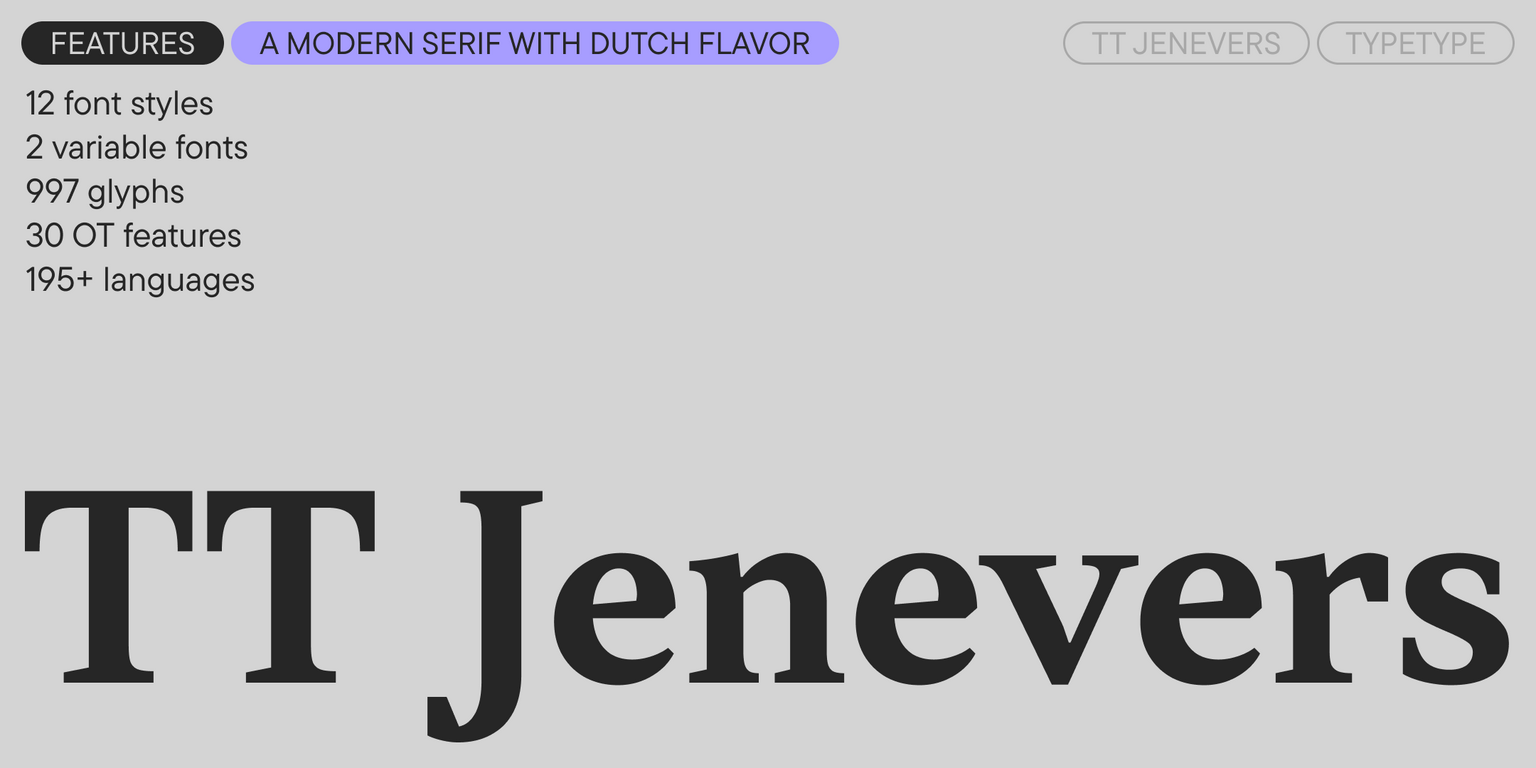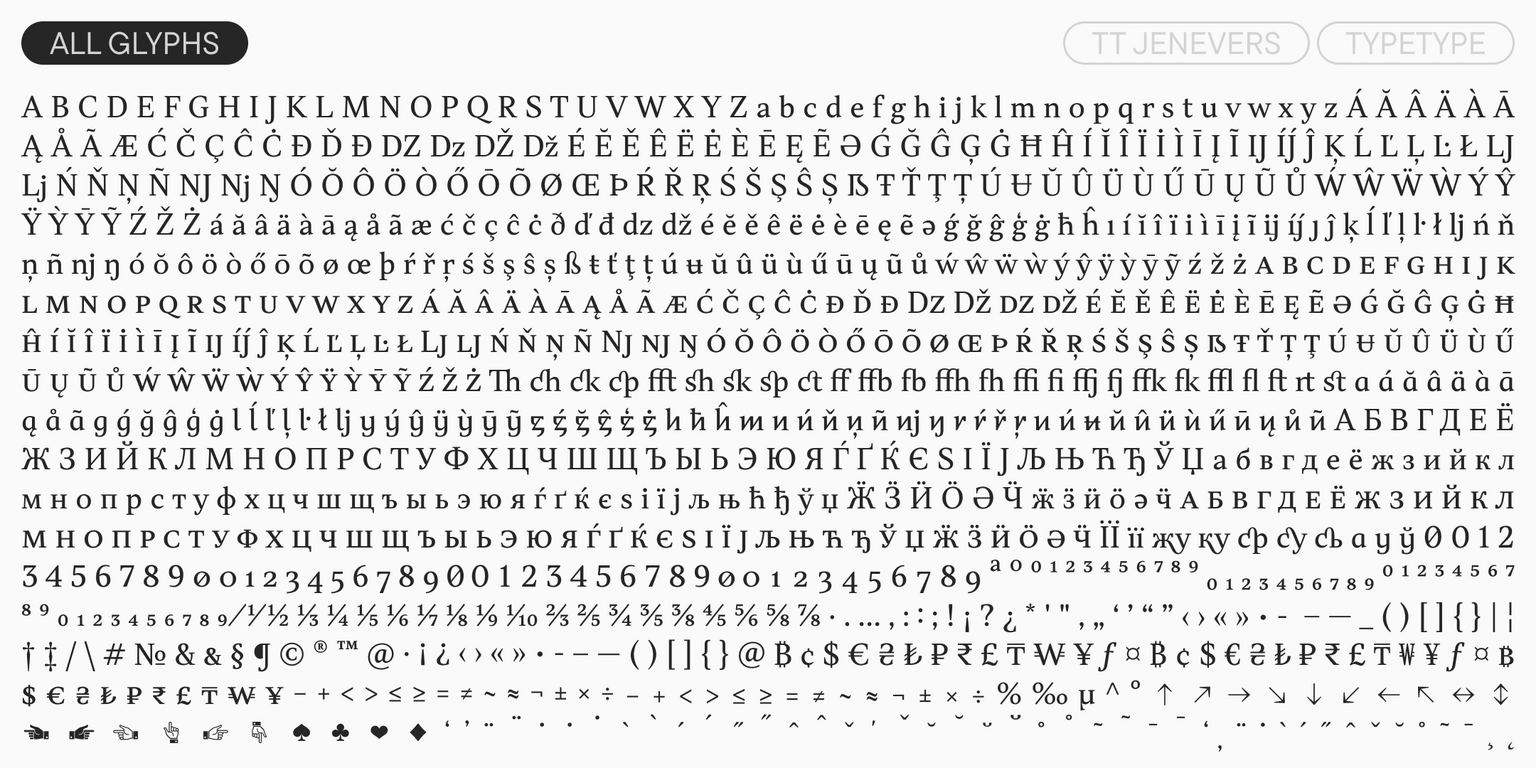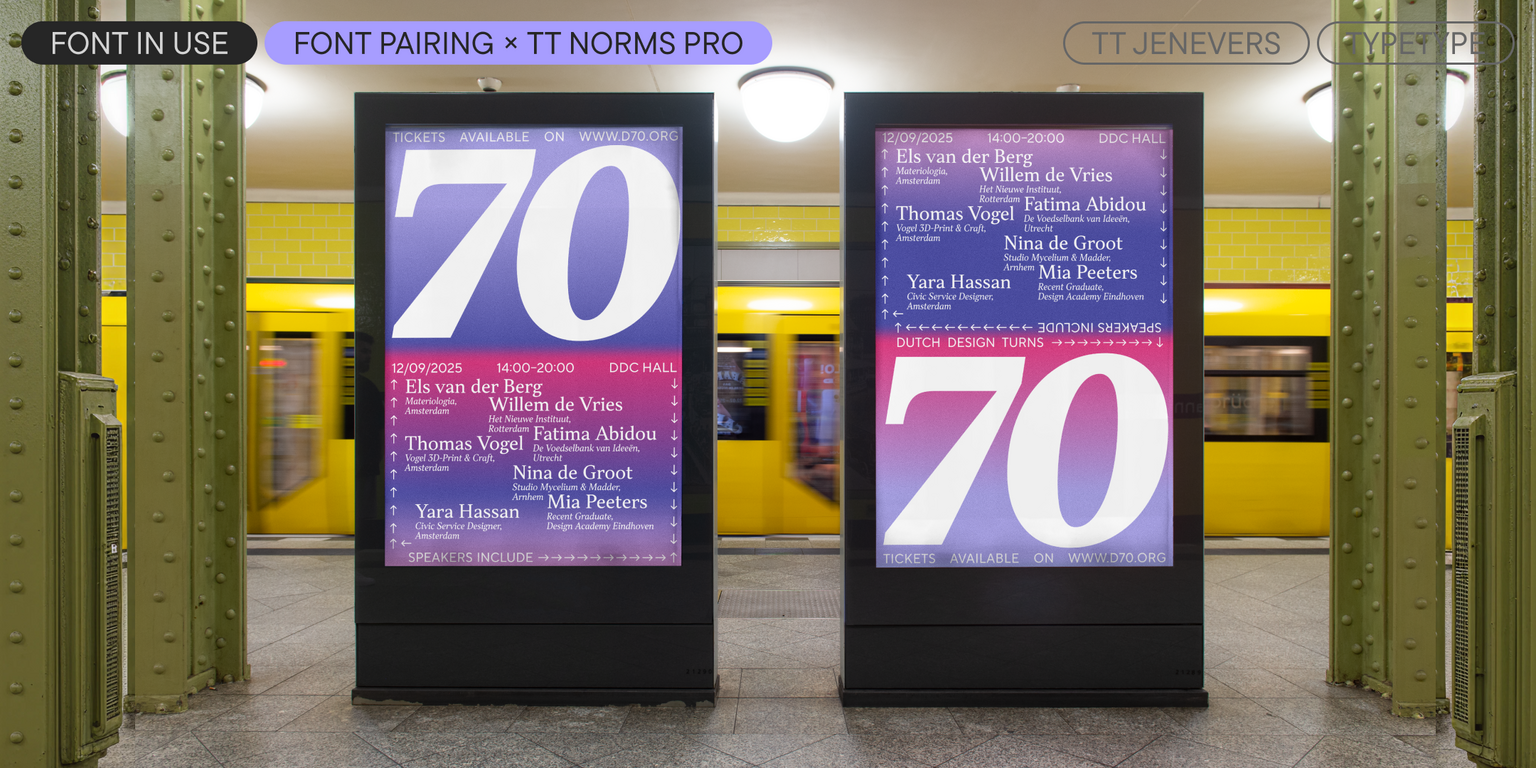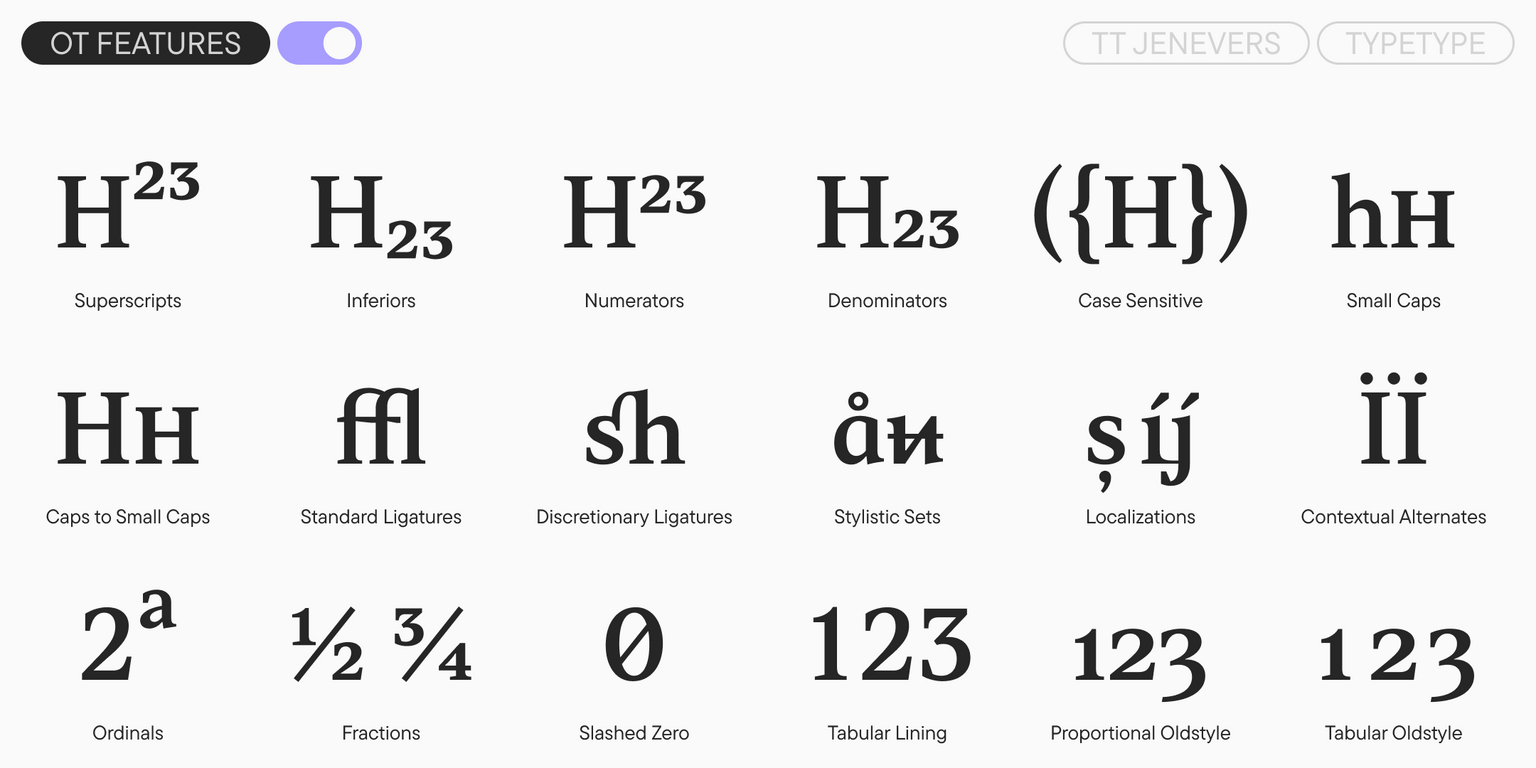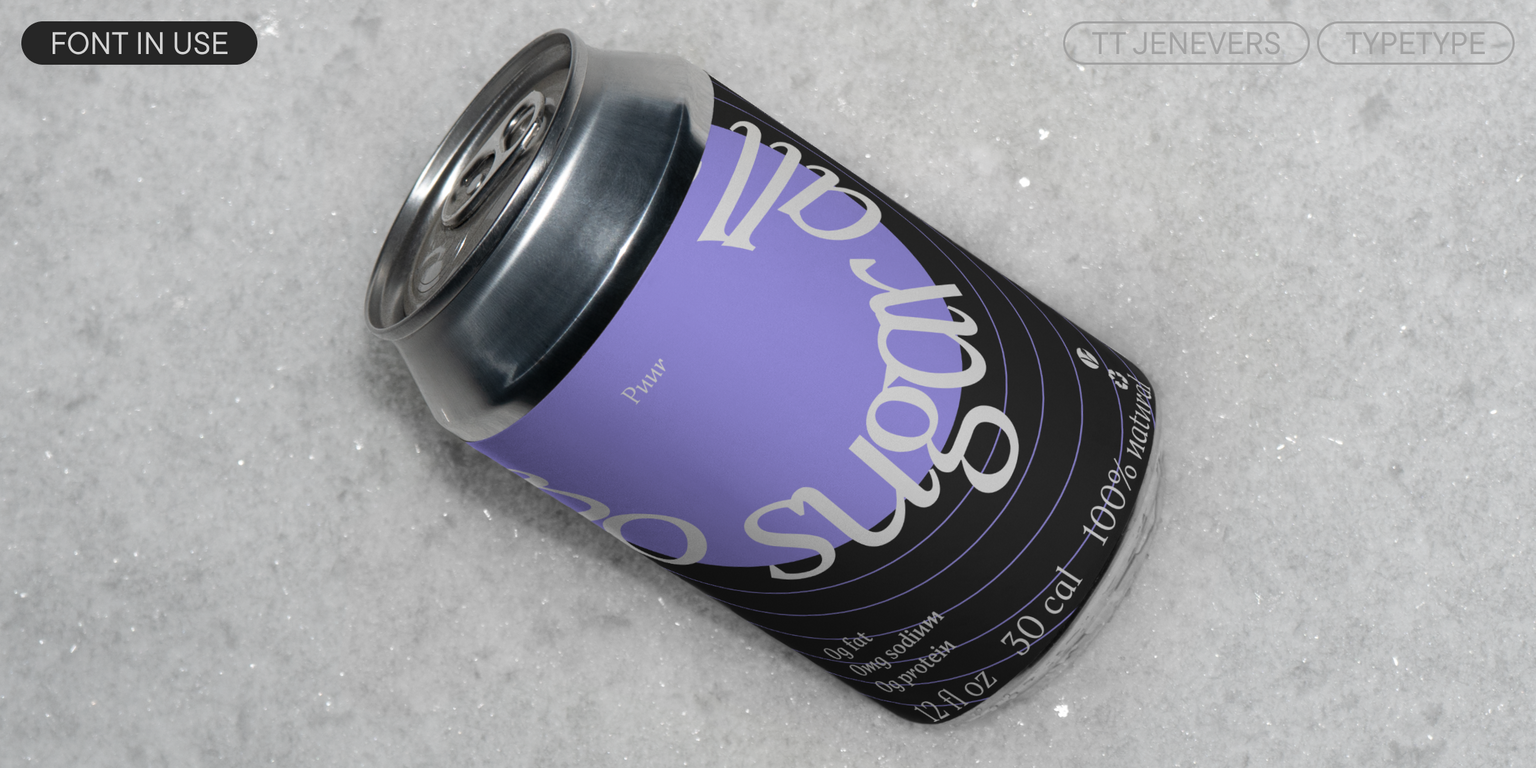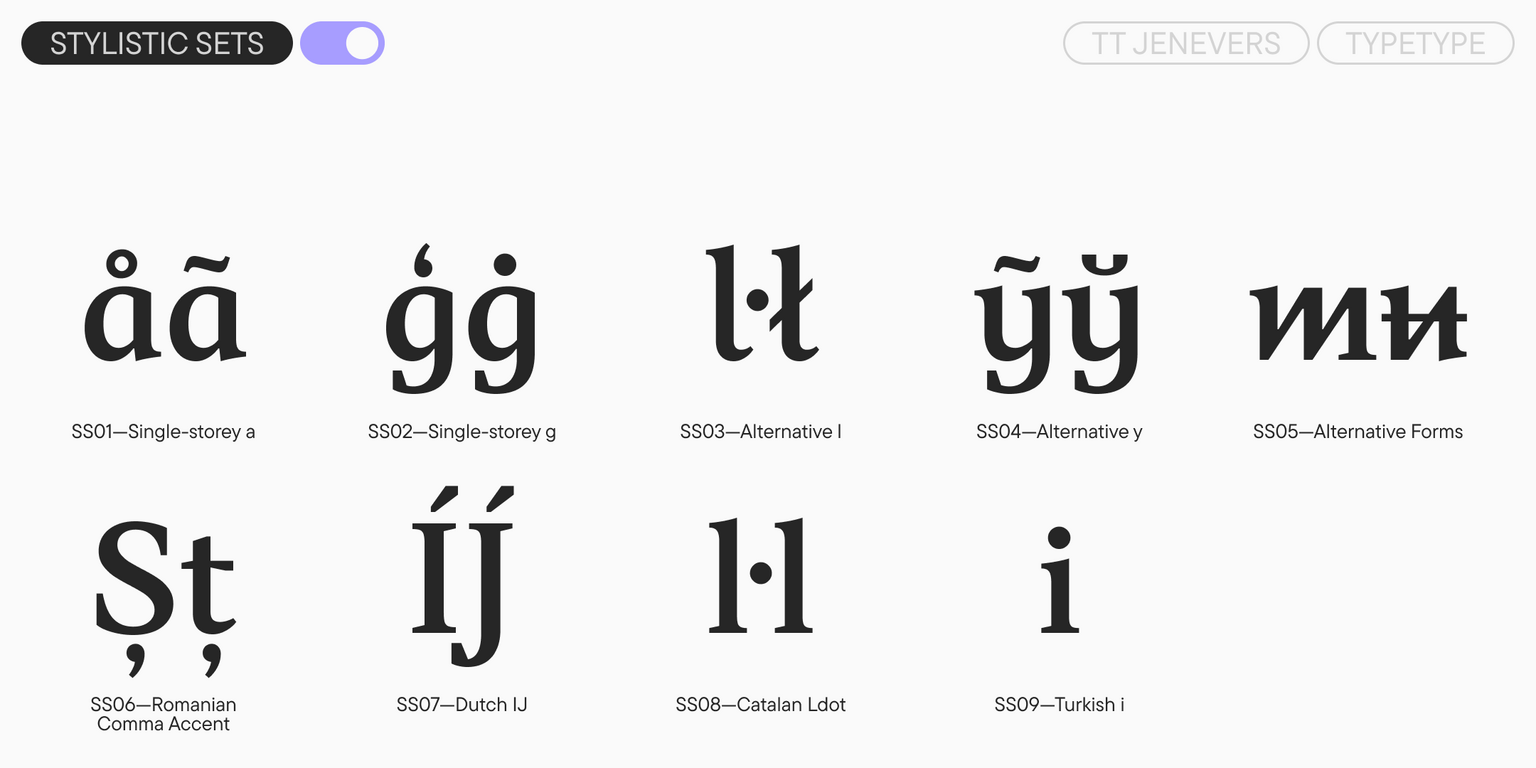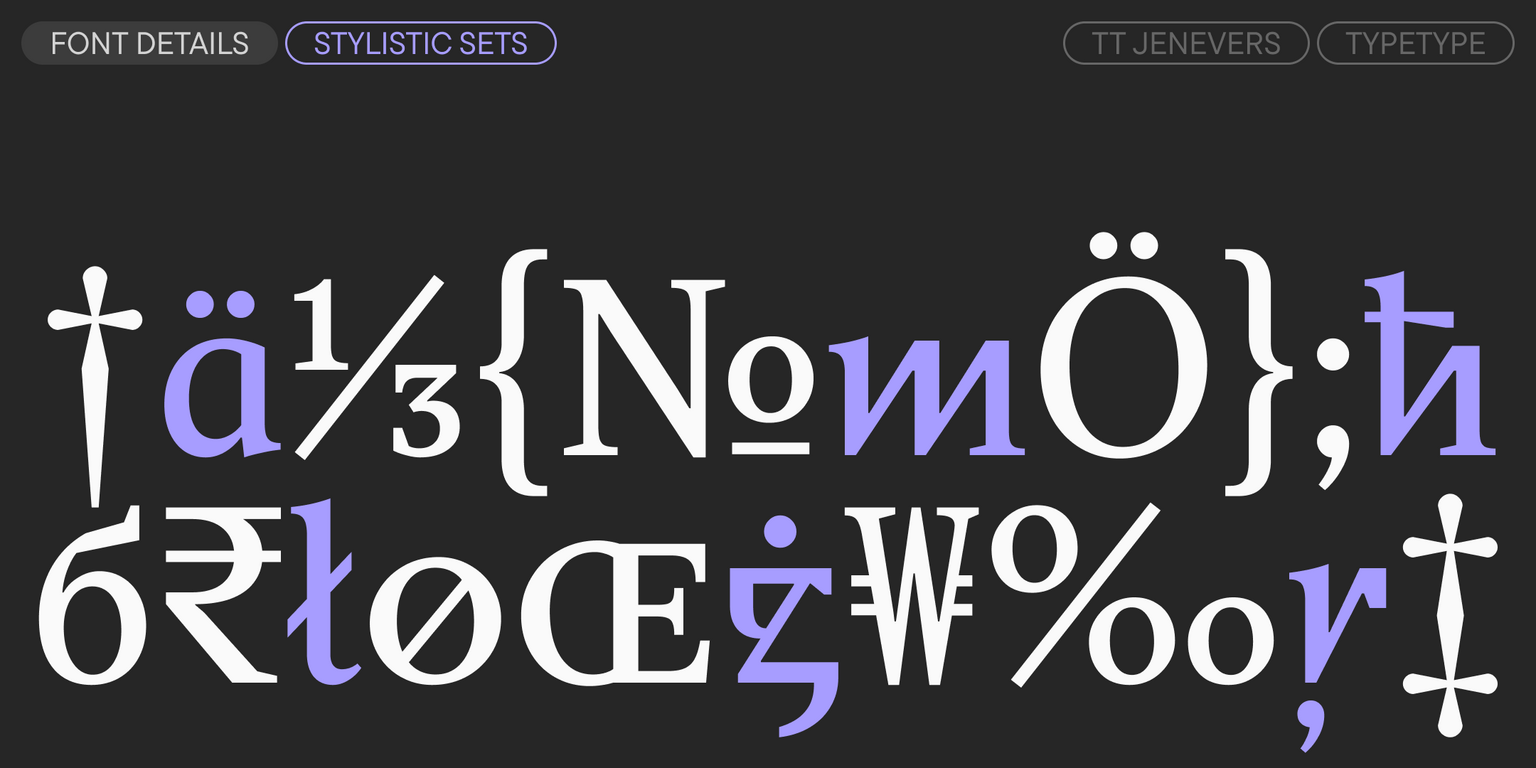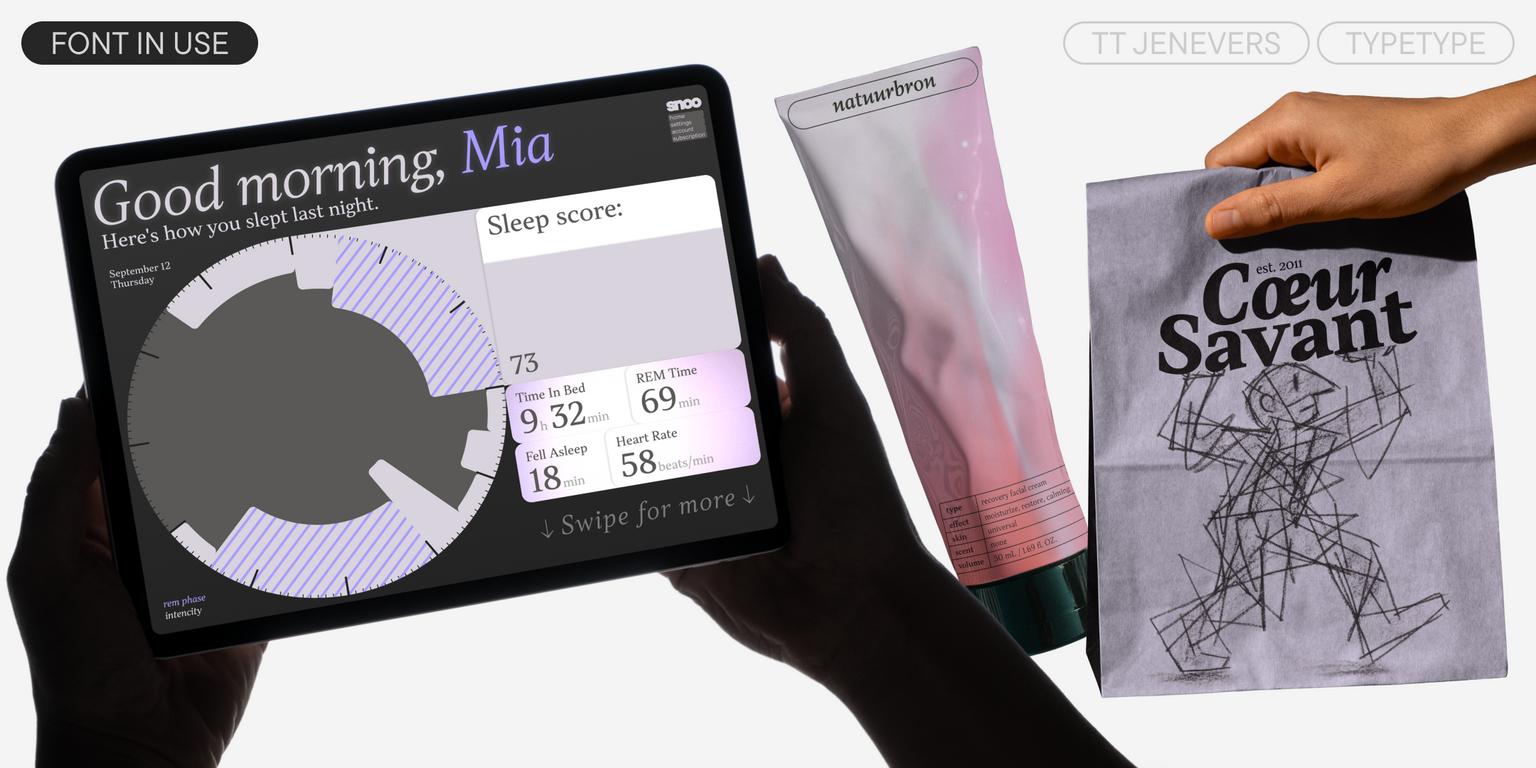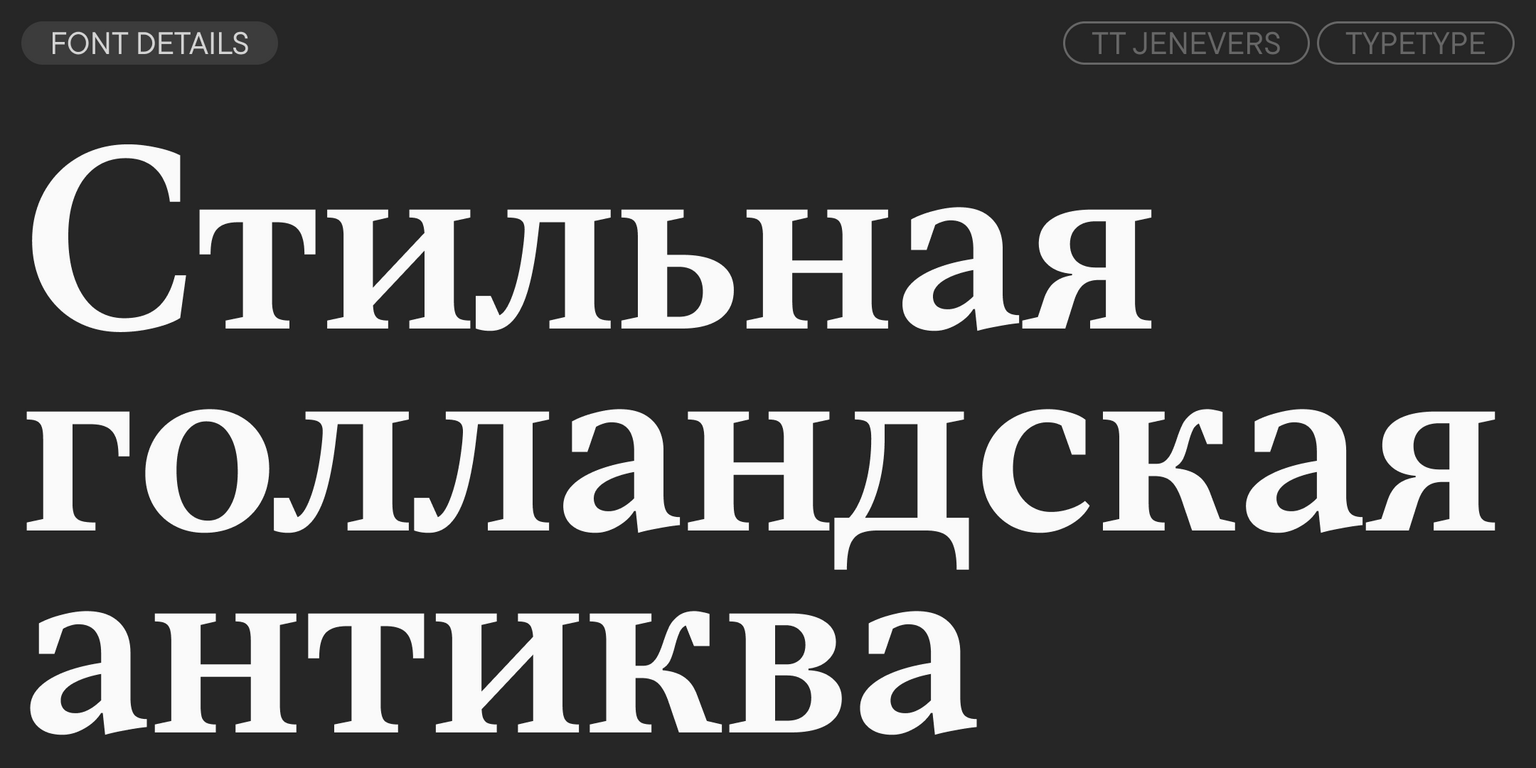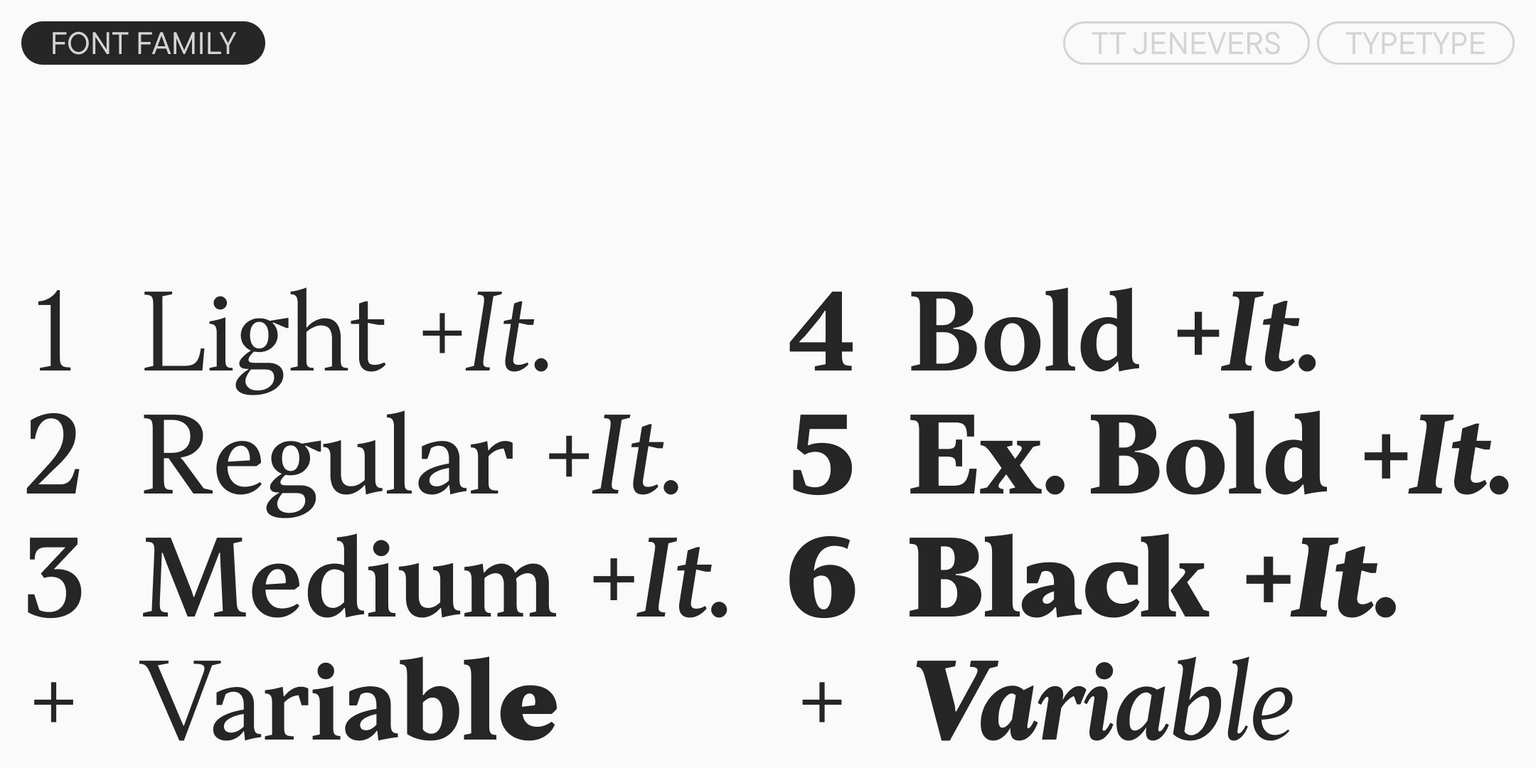
TT Jenevers
TT Jenevers — ТТ Женеверс
Произносится «ТТ Женеверс». «Jenevers» — производное слово от jenever, в переводе с голландского «женевер». Буквы «TT» являются аббревиатурой названия компании.
TT Jenevers — акцидентная голландская антиква с характерными деталями, такими как ассиметричные засечки и нерегулярный наклон овалов.
TT Jenevers
Голландская антиква нового стиля
TT Jenevers
В букве «о» наклона нет, в p-q он присутствует. В TT Jenevers большие размеры строчных и прописных знаков, что делает гарнитуру достаточно акцидентной. В то же время, большой полуовал у строчных знаков не даёт буквам залипать, что позволяет использовать TT Jenevers в текстовых наборах.
TT Jenevers
В гарнитуре присутствуют характерные детали, свойственные голландским антиквам
TT Jenevers
Курсивные начертания TT Jenevers немного заужены по отношению к прямым начертаниям
TT Jenevers
Вариативность
О гарнитуре TT Jenevers
Встречайте TT Jenevers версии 1.200!
Обновили шрифт: добавили новые знаки, фичи, языки и вариативные начертания, а также усовершенствовали техническую составляющую гарнитуры.
TT Jenevers относится к голландским новостильным антиквам. В нём есть характерные детали, свойственные этому типу шрифтов: например, ассиметричная форма засечек и нерегулярный наклон овалов. Так, в букве «о» наклона нет, а в «p» и «q» он присутствует. Курсивные начертания, входящие в гарнитуру, немного заужены по отношению к прямым — это сделано для большей плотности текстового набора.
В TT Jenevers есть пять стилистических сетов, которые позволяют менять характер шрифта — сделать его более рукописным или добавить остроты и футуристичности. Также в гарнитуру входит капитель для кириллицы и латиницы, лигатуры, стандартные и старостильные цифры и другие полезные фичи.
В обновлённой версии увеличился кассовый состав — в частности, появились дроби. Функциональность гарнитуры значительно расширилась благодаря двум новым вариативным шрифтам — для прямого и наклонного весов. А ещё мы сделали детальную ручную ревизию кернинга и добавили ручной хинтинг для всех начертаний.
Гарнитура достаточно универсальна в применении. Большие размеры строчных и прописных знаков придают TT Jenevers акцидентности. В то же время большой полуовал у строчных знаков не даёт буквам залипать, что позволяет использовать шрифт в текстовых блоках.
В TT Jenevers версии 1.200 входит:
• 14 начертаний: 6 прямых, 6 тру-италиков и 2 вариативных шрифта;
• 997 знаков в каждом начертании;
• 30 OpenType фич;
• Поддержка 195 языков.
TT Jenevers — антиква, которая умеет удивлять!
Что изменилось в шрифте:
• Общее количество начертаний выросло с 12 до 14;
• Появилось два новых вариативных начертания для прямого и наклонного весов — TT Jenevers VF Upright и TT Jenevers VF Italic;
• Общее количество знаков в каждом начертании выросло с 877 до 997;
• В частности, появились дроби;
• Количество поддерживаемых языков увеличилось со 180 до 195;
• Количество OpenType фич выросло с 24 до 30;
• Мы сделали детальную ручную ревизию кернинга во всех начертаниях;
• Добавили ручной хинтинг для всех начертаний.
ss05 | Alternative Forms
smcp | Small Caps
liga | Standard Ligatures
onum | Oldstyle Figures
dlig | Discretionary Ligatures
case | Case Sensitive Forms